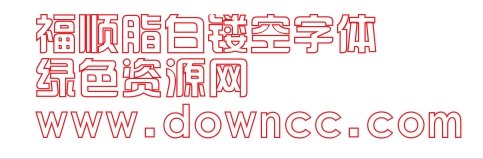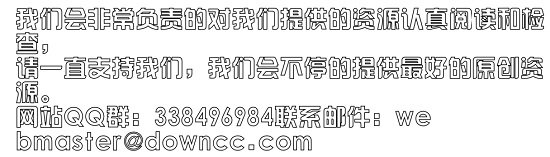
福順脂白鏤空字體是一款筆畫之間更加連貫的空心字體,結(jié)構(gòu)更為緊湊、字體大小比較統(tǒng)一,給人端正威嚴(yán)的視覺體驗(yàn),喜歡制作鏤空文字的朋友就可以來試試哦!
本字體與福順方塊積木字體比較類似,不過脂白鏤空體結(jié)構(gòu)更加端正,字體造型更加清晰鮮艷,適合制作一些logo、商標(biāo)等問題,鏤空的設(shè)計給人醒目的視覺體驗(yàn)。
脂白鏤空字體免去了人工設(shè)置空心字體的繁瑣體驗(yàn),讓文字更加直觀顯眼,字庫完整,滿足大家常規(guī)的中英文和繁簡體輸入,用于平面設(shè)計、海報設(shè)計等方面,效果比較顯著!